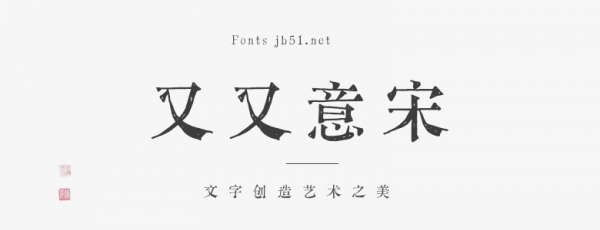
又又意宋,基于傳統(tǒng)鉛字宋體及古刻本開發(fā)的手寫宋體,風(fēng)格古意中帶一點(diǎn)詼諧,適合應(yīng)用于藝術(shù)設(shè)計(jì)、平面宣傳設(shè)計(jì)、網(wǎng)頁設(shè)計(jì),書法字帖等領(lǐng)域.
適用風(fēng)格:適用于排版古典詩詞,古風(fēng)設(shè)計(jì),標(biāo)題及內(nèi)文皆適合
符合GB 2312標(biāo)準(zhǔn)6763個(gè)簡體漢字,配有相應(yīng)風(fēng)格的英文以及標(biāo)點(diǎn)